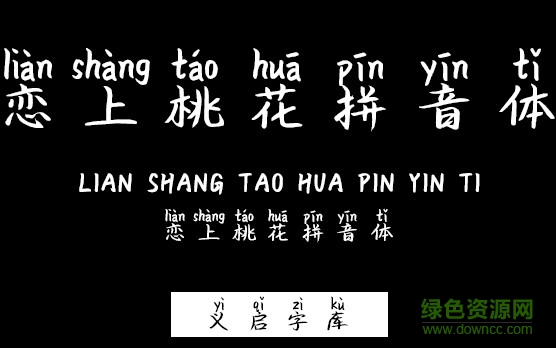
義啟戀上桃花拼音字體
義啟戀上桃花拼音體是一款非常有特色的義啟字體,這款字體類似于手寫體,字形結構優(yōu)美大方,獨具特色,喜歡的朋友歡迎來綠色資源網免費下載使用!
義啟戀上桃花拼音體
戀上桃花拼音體簡介
戀上桃花,戀上你,余生很長,何必慌張。
戀上桃花拼音體特點
1、字形方正,重心偏高;
2、連筆較少,抬筆圓滑;
3、文字簡潔,平靜和諧;
4、字風溫柔,沒有凌厲的感覺;
5、自動添加拼音,方便認字。